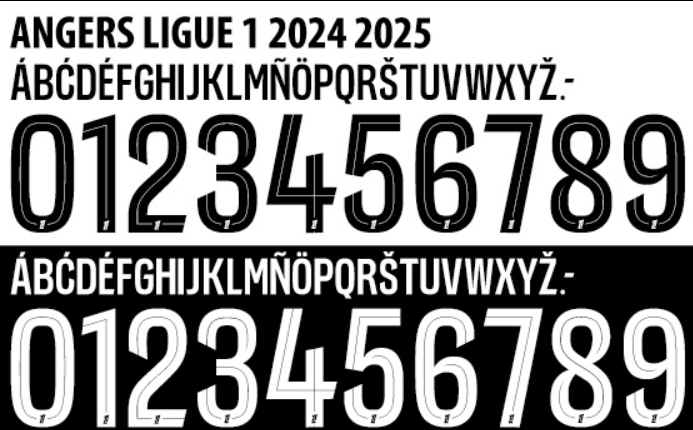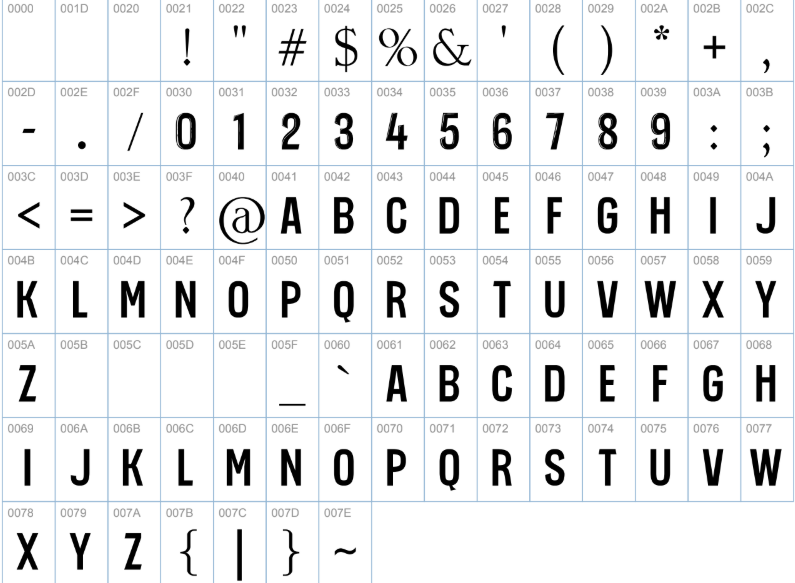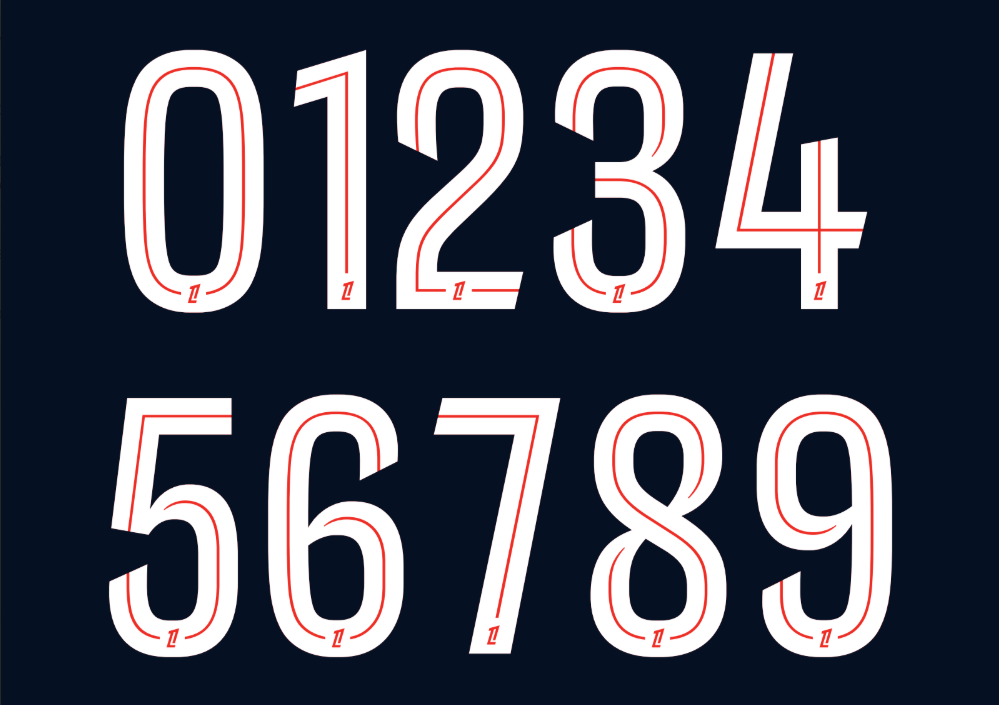
A temporada 2024/2025 marca uma revolução visual no Campeonato Francês. Com o rebranding completo da competição (agora Ligue 1 McDonald’s), foi introduzida uma tipografia totalmente inédita, obrigatória para todos os clubes da elite, desde o poderoso Paris Saint-Germain (PSG) até o tradicional Olympique de Marseille.
Estilo Visual: Modernidade e Geometria
A nova fonte da Ligue 1 foi desenhada para acompanhar o novo logotipo minimalista da competição. Esqueça as bordas arredondadas e o visual “bolha” das temporadas passadas.
A versão 2024/2025 aposta em uma estética Geométrica e Industrial. Os números possuem cortes angulares agressivos e uma estrutura sólida, garantindo excelente legibilidade tanto nas transmissões 4K quanto nas arquibancadas. É uma fonte que conversa perfeitamente com os templates modernos da Nike, Adidas e Puma utilizados pelos clubes franceses, transmitindo força e inovação tecnológica.